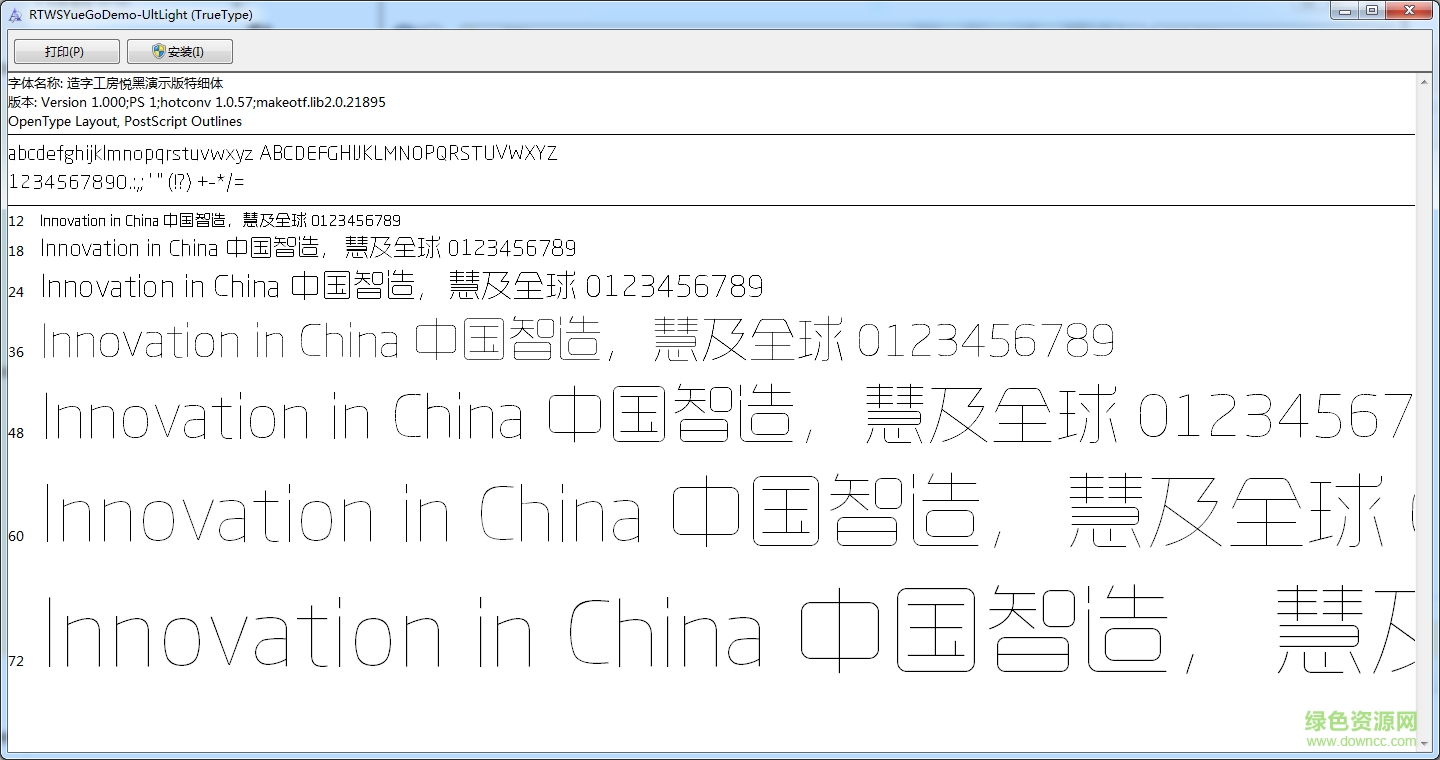
软件介绍 软件标签: 造字工房 造字工房悦黑演示版特细体是一款简洁大气的win细体,此款字体线条较细,清醒爽目,拥有完整的字库,结构简洁,易读性强,安装简单方便,使用范围非常广泛,喜欢的朋友欢迎来绿色资源网下载!字体安装方法方法一:控制面板/字体/文件/安装新字体;方法二:直接将字体复制到C:\WINDOWS\Fonts。方法三:针对win7系统,用户只需选中字体右键安装即可。注意事项本站所有字体资源仅供个人学习与参考,如需商业使用请到相关官网授权。 软件截图 上一张下一张(1 / 1) 安装详细截图 其他版本下载 标题 大小 更新日期 下载 下载地址 电脑版 造字工房悦黑演示版细体 点击报错 软件无法下载或下载后无法使用,请点击报错,谢谢! 关闭报错反馈 请描述您所遇到的错误,我们将尽快予以修正,谢谢! *必填项,请输入内容 本类最新 dreamweaver字体库 首尔南山体字体 v1.06 官方版 潮字社风云简ttf 潮字社凌渡鲲鹏简体字体 潮字社曾玉波手书简字体 微博慧心字体 相关文章 小米3后盖怎么打开?小米3正确开盖方式演示图解 ppt转换成word,演示文稿转换文档方法 WPS演示幻灯片循环播放方法 无线共享打印!演示路由打印全过程 用Flash Cam制作演示动画 用户评论 热门评论 最新评论 发表评论 查看所有评论(0) 昵称: 请不要评论无意义或脏话,我们所有评论会有人工审核. 字数: 0/500 (您的评论需要经过审核才能显示)